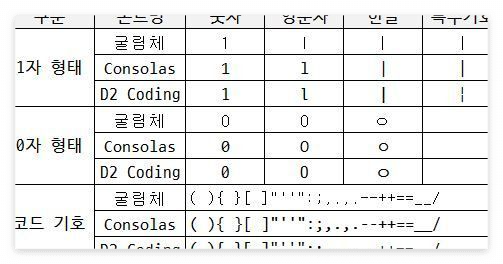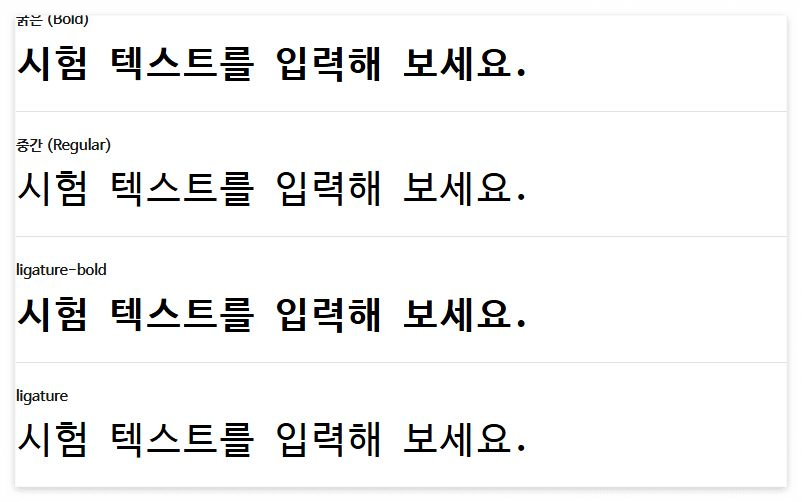
나눔고딕 D2 Coding은 네이버가 제공하는 고정폭 코딩 전용 글꼴로, 개발자의 작업 효율성과 가독성을 극대화하기 위해 설계된 서체입니다.
나눔고딕 D2 Coding의 특징과 장점
나눔고딕 D2 Coding은 단순한 코딩 폰트를 넘어, 개발 환경에 특화된 다양한 기능과 디자인적 장점을 제공합니다.
1. 가독성 최적화
D2 Coding 글꼴은 나눔바른고딕을 기반으로 제작되어 영어, 숫자, 한글, 특수문자의 가독성을 크게 강화했습니다.
특히, 유사한 문자(예: O와 0, I와 l) 간의 구분이 명확하게 되어 있어 긴 코드를 읽거나 디버깅할 때 효율적입니다.
2. 고정폭 설계
고정폭(모노스페이스) 글꼴로 제작되어 코드의 정렬이 완벽하게 유지됩니다.
이는 다양한 개발 도구와 IDE 환경에서 일관된 자간과 행간을 제공하여 작업의 편의성을 높입니다.
3. 한글과의 조화
한글 디자인에도 신경을 써서 영어와 한글이 혼재된 코드 작성 시에도 시각적 조화를 유지합니다.
이는 다른 고정폭 글꼴에서는 보기 드문 D2 Coding만의 강점입니다.
4. 다양한 굵기 옵션
D2 Coding은 Regular, Bold와 함께 ligature 지원 버전을 제공합니다.
이로 인해 일반적인 코딩 환경뿐만 아니라 디자인적으로도 유연하게 사용할 수 있습니다.
| 굵기 옵션 | 주요 특징 및 활용 |
|---|---|
| Regular | 기본적인 코딩 작업에 적합 |
| Bold | 강조가 필요한 부분에 유용 |
| Ligature | 디자인 요소를 활용한 직관적 표현 |
| Ligature Bold | 가독성을 높인 세련된 스타일 |
나눔고딕 D2 Coding의 활용 방안
1. IDE 및 텍스트 편집기에서의 사용
D2 Coding은 IntelliJ, VS Code, Eclipse와 같은 IDE에서 사용하기에 최적화된 폰트입니다.
고정폭 특성과 유사 문자 간의 명확한 구분 덕분에 코드 작성과 디버깅이 한층 수월해집니다.
2. 터미널 및 CLI 환경
터미널에서도 D2 Coding은 탁월한 가독성을 제공합니다.
많은 글꼴이 터미널에서의 사용성을 간과하지만, D2 Coding은 자간과 행간이 균형 잡혀 있어 장시간 작업에도 눈의 피로를 줄여줍니다.
3. 한글 문서 기반의 프로그래밍
한국어 주석을 자주 사용하는 개발자에게 D2 Coding은 최고의 선택입니다.
한글과 영어가 자연스럽게 어우러져 코드 작성 중 시각적 일관성이 유지됩니다.
4. 디자이너를 위한 활용
코딩 폰트라는 한계를 넘어, D2 Coding은 디자인 작업에도 활용할 수 있습니다.
특히, ligature 버전은 현대적인 타이포그래피 작업에 적합하며, 특수 문자를 활용한 프로젝트에서도 유용합니다.
나눔고딕 D2 Coding 사용 후기
D2 Coding을 직접 사용해 본 결과, 가독성과 작업 효율성 측면에서 뛰어난 성능을 발휘합니다.
특히, 숫자와 알파벳 간의 변별력이 높아 코드를 빠르게 읽고 분석할 수 있었습니다.
또한, 한국어와 영어가 혼합된 코드에서 문장의 시각적 정렬이 깔끔하게 유지되며, 터미널 환경에서도 완벽한 자간과 행간을 보여줍니다.
이 모든 점에서 D2 Coding은 단순히 무료 폰트를 넘어선 유용한 도구로 자리 잡았습니다.
마치며
나눔고딕 D2 Coding은 개발자를 위한 완벽한 폰트입니다.
고정폭 설계, 뛰어난 가독성, 유사 문자 변별력, 한글과의 조화 등 다양한 강점을 지닌 D2 Coding은 개발 환경에서의 필수적인 선택이 될 것입니다.